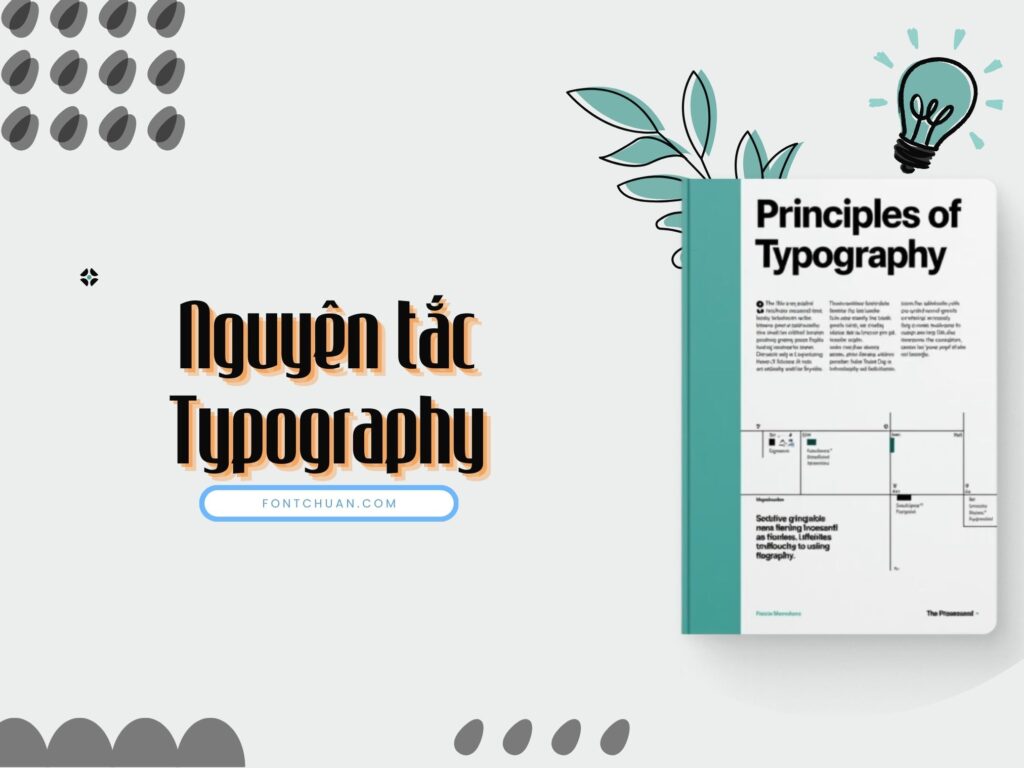
Nguyên Tắc Typography: Hướng dẫn toàn diện từ chuyên gia
Trong thế giới thông tin bùng nổ ngày nay, nơi mỗi từ ngữ đều mang một trọng lượng nhất định, có một yếu tố thầm lặng nhưng vô cùng mạnh mẽ định hình cách chúng ta tiếp nhận và tương tác với nội dung: đó chính là typography. Vượt xa việc lựa chọn một font chữ đơn thuần, typography là nghệ thuật và khoa học của việc sắp xếp chữ để tạo nên sự rõ ràng, dễ đọc và sức hấp dẫn thị giác. Bài viết này sẽ đưa bạn khám phá những nguyên tắc cốt lõi, từ cơ bản đến nâng cao, giúp bạn khai thác tối đa tiềm năng của chữ viết trong mọi thiết kế.
Giới thiệu Typography
Typography (thiết kế chữ) là nghệ thuật sắp xếp và trình bày các ký tự (font chữ, kiểu chữ) trong một bố cục vừa dễ đọc vừa có tính thẩm mỹ. Bằng cách khéo léo kết hợp kiểu chữ, cỡ chữ và khoảng cách, nhà thiết kế có thể biến văn bản thành thông điệp ấn tượng phục vụ nhiều dạng thiết kế khác nhau (từ website, brochure đến ấn phẩm in ấn). Trong môi trường kinh doanh cạnh tranh, việc sử dụng Typography đúng cách giúp thương hiệu tạo bản sắc riêng, thu hút sự chú ý của khách hàng và truyền tải thông điệp một cách hiệu quả.
Vai trò của Typography trong thiết kế
Trong các dự án thiết kế, Typography đóng vai trò then chốt trong việc truyền tải thông điệp và nâng cao trải nghiệm người dùng (UI/UX). Một khảo sát cho thấy khoảng 95% nội dung giao diện web là chữ, do đó tối ưu Typography đồng nghĩa với tối ưu trải nghiệm người dùng. Theo các chuyên gia, Typography mang lại nhiều lợi ích như:
• Giúp nội dung dễ đọc hơn, tăng tỷ lệ tương tác và nâng cao trải nghiệm người dùng.
• Để lại ấn tượng tốt và tăng nhận diện thương hiệu nhờ lựa chọn kiểu chữ, bố cục và phân cấp phù hợp.
• Giúp giữ chân người đọc ở lại trang lâu hơn bằng cách dẫn dắt nội dung theo thứ tự ưu tiên (các phần quan trọng được làm nổi bật).
• Truyền tải thông điệp chính xác và hiệu quả, tránh làm người đọc xao lãng.
Nói cách khác, Typography không chỉ đơn thuần là “chữ đẹp” mà còn là công cụ mạnh mẽ giúp biến văn bản thành thông điệp có sức ảnh hưởng, góp phần định hình cá tính và giá trị của thương hiệu.
Nguyên tắc cốt lõi trong thiết kế Typography
Typography tuân theo nhiều nguyên tắc thiết kế nhằm đảm bảo tính thẩm mỹ và hiệu quả truyền đạt. Dưới đây là một số nguyên tắc cơ bản cần lưu ý:
Lựa chọn typeface phù hợp
Font chữ là yếu tố đầu tiên định hình cảm xúc và thông điệp thị giác.
• Chọn theo mục đích sử dụng: Thiết kế đơn giản → dùng ít font, rõ ràng; dự án phức tạp → cần phối hợp linh hoạt.
• Font phải phản ánh đúng ngữ điệu thương hiệu: vui tươi ≠ nghiêm túc.
• Ưu tiên chọn font cho body text trước vì đây là phần chiếm tỷ trọng lớn, cần dễ đọc, ít mỏi mắt.
• Phối hợp font: Dùng 1–2 font là lý tưởng. Phối Serif & Sans-serif có cấu trúc tương đồng giúp tạo tương phản nhẹ mà vẫn hài hòa.
Khoảng cách chữ và dòng
Tối ưu khoảng cách giúp văn bản dễ đọc, giảm gánh nặng thị giác.
• Kerning: Điều chỉnh thủ công khoảng cách giữa 2 ký tự, dùng cho tiêu đề, logo.
• Tracking: Dãn/nén đều khoảng cách toàn khối chữ, kiểm soát mật độ văn bản.
• Leading: Khoảng cách dòng nên bằng 120–150% cỡ chữ để tạo nhịp đọc dễ chịu.
Hạn chế phụ thuộc vào thiết lập mặc định của phần mềm – cần điều chỉnh thủ công để đạt hiệu quả tối ưu.
Căn chỉnh văn bản (Alignment)
Căn lề định hình cách mắt đọc và cảm nhận bố cục.
• Căn trái: Dễ đọc nhất, phù hợp cho đoạn dài.
• Căn phải / giữa: Dùng cho tiêu đề ngắn, trích dẫn – tạo điểm nhấn.
• Căn đều 2 bên: Trang trọng nhưng cần kiểm soát “khoảng sông trắng”.
Bảng dưới đây trình bày các kiểu căn chỉnh và bối cảnh ứng dụng phù hợp:
Kiểu Căn Chỉnh Đặc điểm Ưu điểm Nhược điểm/Lưu ý Bối cảnh ứng dụng
Căn trái Đường biên trái thẳng, biên phải không đều Dễ đọc nhất, tạo dòng chảy tự nhiên, phù hợp với thói quen đọc Có thể để lại khoảng trống không đều ở lề phải Phần thân văn bản (body text), bài viết, sách, báo
Căn phải Đường biên phải thẳng, biên trái không đều Tạo nét độc đáo, phù hợp cho văn bản ngắn Khó đọc cho đoạn dài, đi ngược thói quen đọc Chú thích, tiêu đề phụ, trích dẫn ngắn, thiết kế nghệ thuật
Căn giữa Cân bằng ở trung tâm, hai biên không đều Thu hút sự chú ý, tạo cảm giác cân đối, trang trọng Yếu ớt nhất, khó đọc cho đoạn dài Tiêu đề, logo, lời mời, thơ, trích dẫn nổi bật
Căn đều hai bên Cả hai biên trái và phải đều thẳng hàng Gọn gàng, chỉn chu, trang trọng, chuyên nghiệp Dễ tạo khoảng cách chữ không đồng nhất (“dòng sông trắng”) Báo, tạp chí, sách (cần điều chỉnh kỹ kerning/tracking)
Phân cấp thông tin (Hierarchy)
Thiết kế phải có thứ tự ưu tiên để định hướng mắt người đọc.
• Dùng kích thước, độ đậm, màu sắc, khoảng cách, kiểu font khác biệt để tạo cấp độ rõ ràng.
• Thiếu phân cấp sẽ khiến toàn bộ văn bản “đồng âm”, gây nhiễu thông tin và giảm hiệu quả truyền đạt.